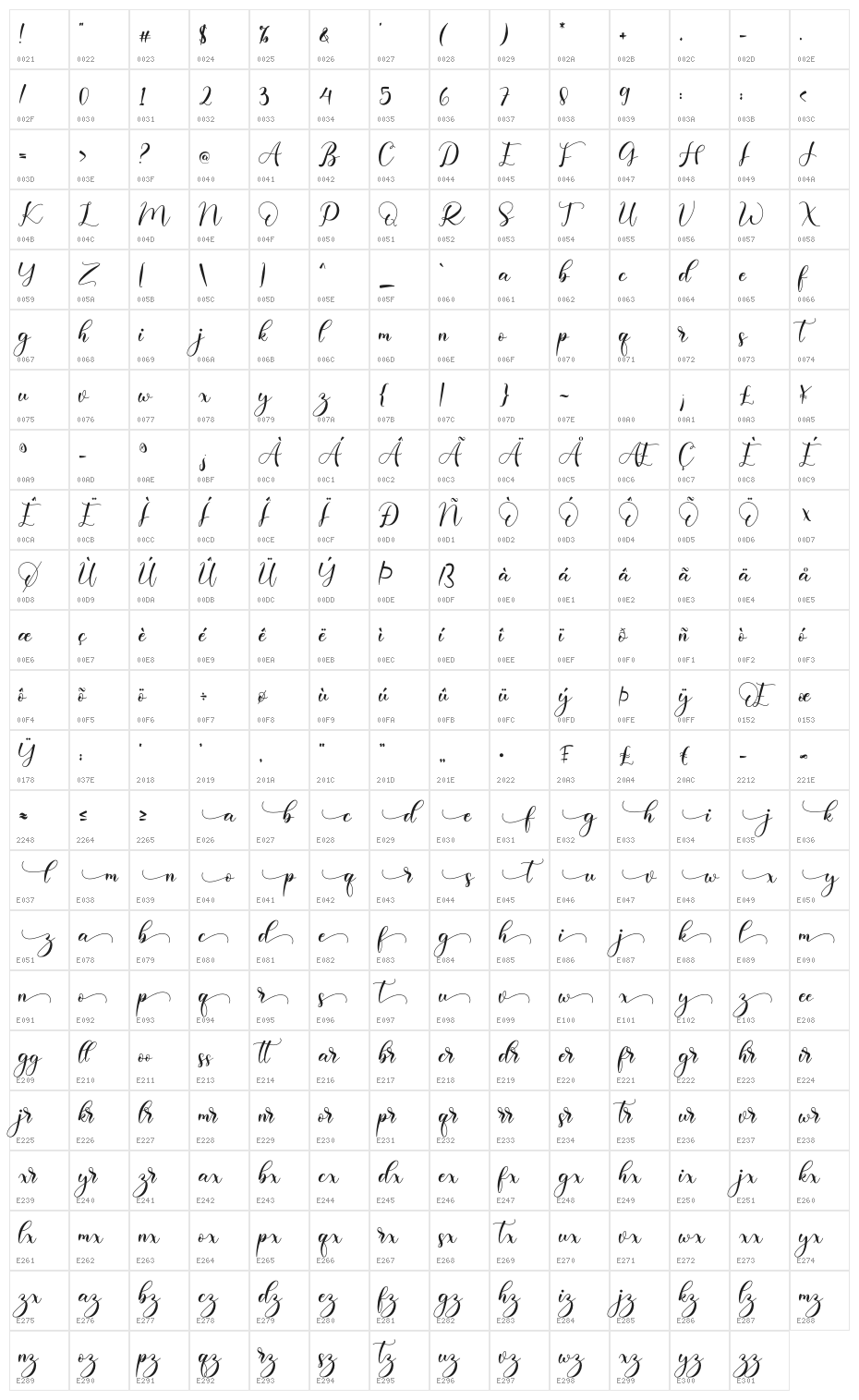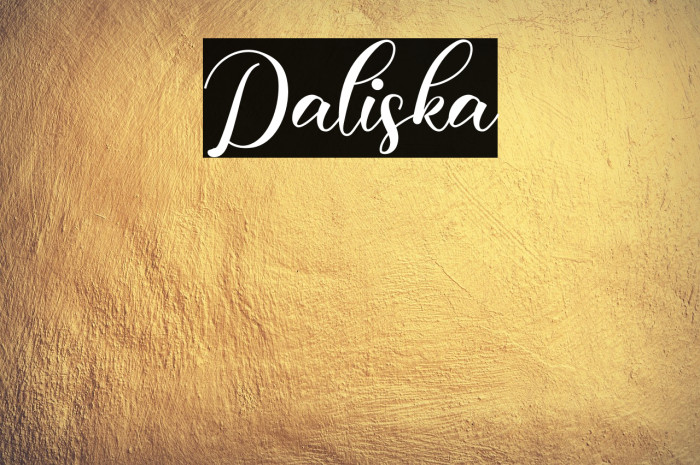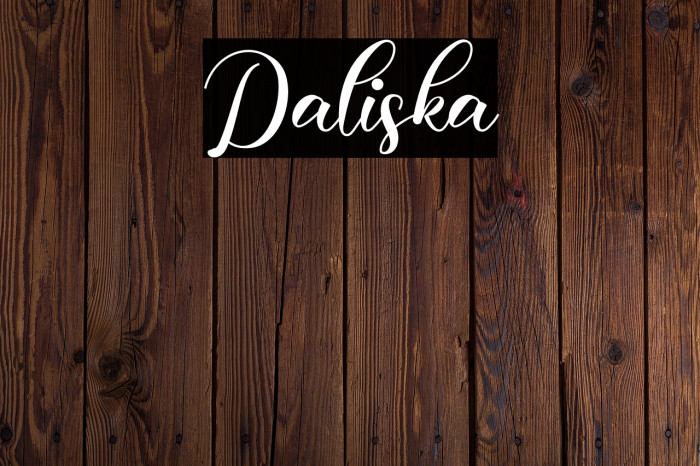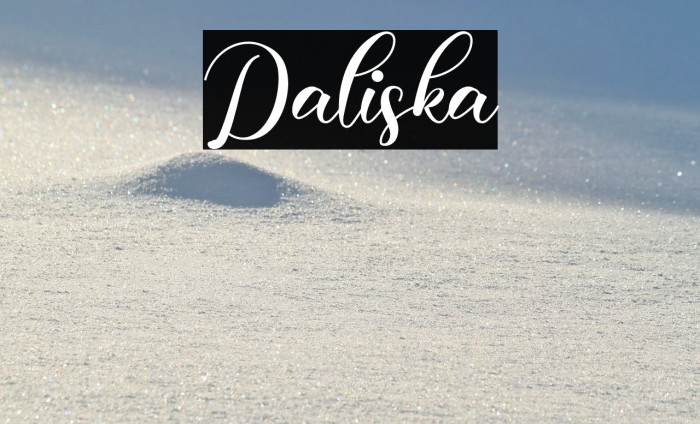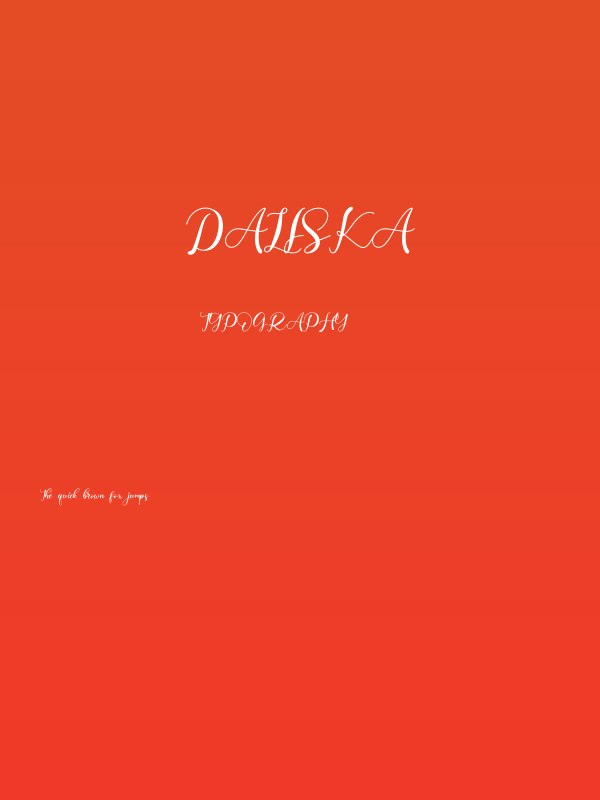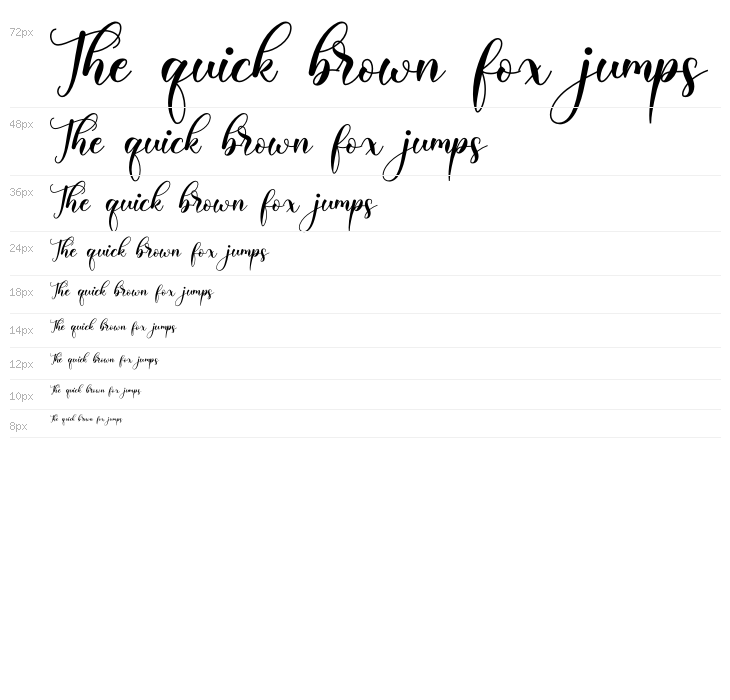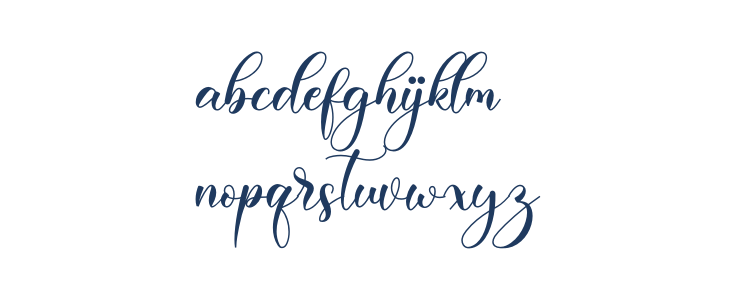
Daliska Font
| Stile generale | Elegant |
| Caso d'uso | Logos, Invitations, Decorative text |
| Progetti proposti | Ideal for wedding invitations, greeting cards, branding, and elegant logo designs. |